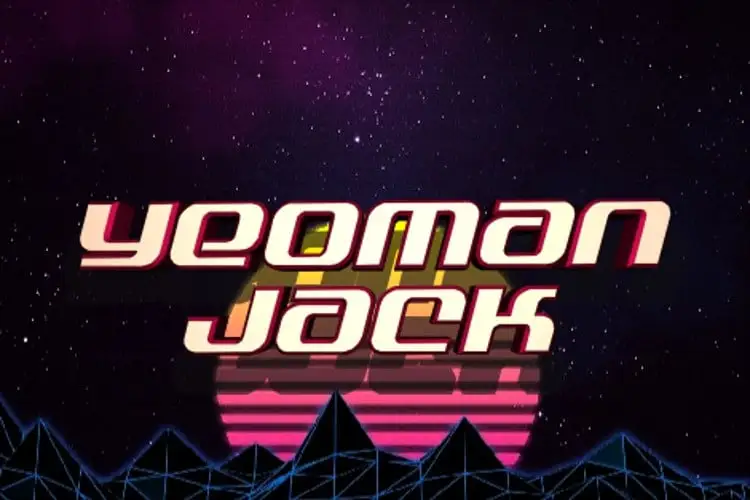
Yeoman Jack Display Font – Download Grátis
A fonte Yeoman Jack Display é uma escolha perfeita para criar elementos visuais dinâmicos e impressionantes. Com seus 26 variações diferentes – incluindo versões regular, italica, semi-italica, hachurada, etc., o Yeoman Jack proporciona a você um arsenal de opções para destacar seu texto em ambientes de design moderno e sofisticado. Com suas variadas configurações de estilo, esta fonte é perfeita para criar uma variedade impressionante de designs. O uso das variações 3D, 3D Italic, Halftone, Halftone Italic, Twotone, Twotone Italic e Gradient cria efeitos visuais vibrantes e atraentes que destacam seus textos em qualquer projeto. Além disso, suas versões como Laser, Laser Italic, Rotated e Rotalic fornecem uma ótima solução para usar seu texto de maneira única, oferecendo um elemento único de identidade visual. Estas são apenas algumas das muitas possibilidades criativas disponíveis com a fonte Yeoman Jack Display. Ela é perfeitamente adaptável à sua necessidade e ao estilo do seu projeto, seja ele editorial, publicitário ou digital – garantindo que cada elemento de texto seja destacado da melhor maneira possível. Sem dúvida, esta font será uma das principais ferramentas em qualquer designer gráfico profissional.